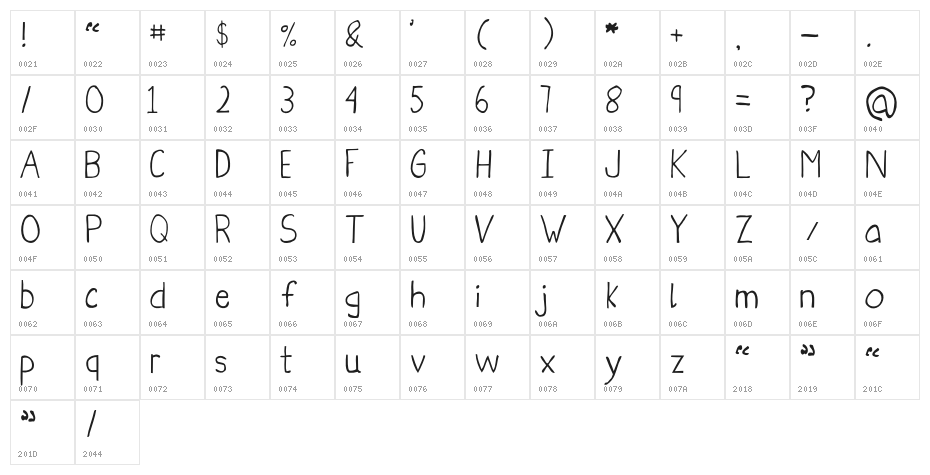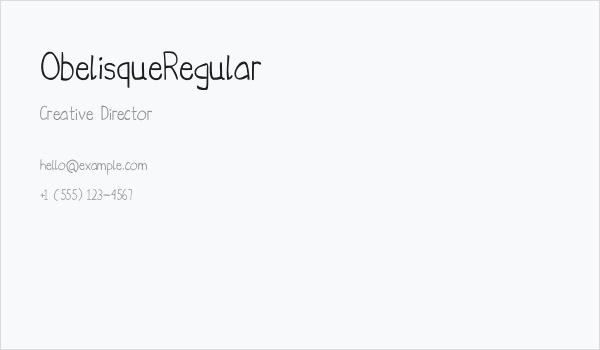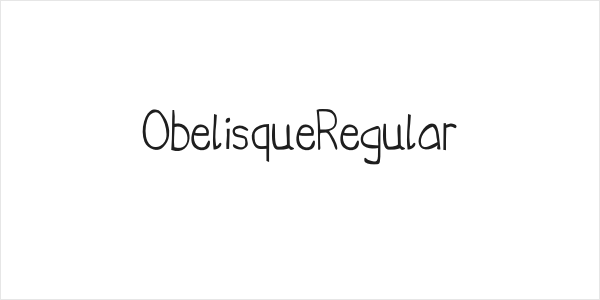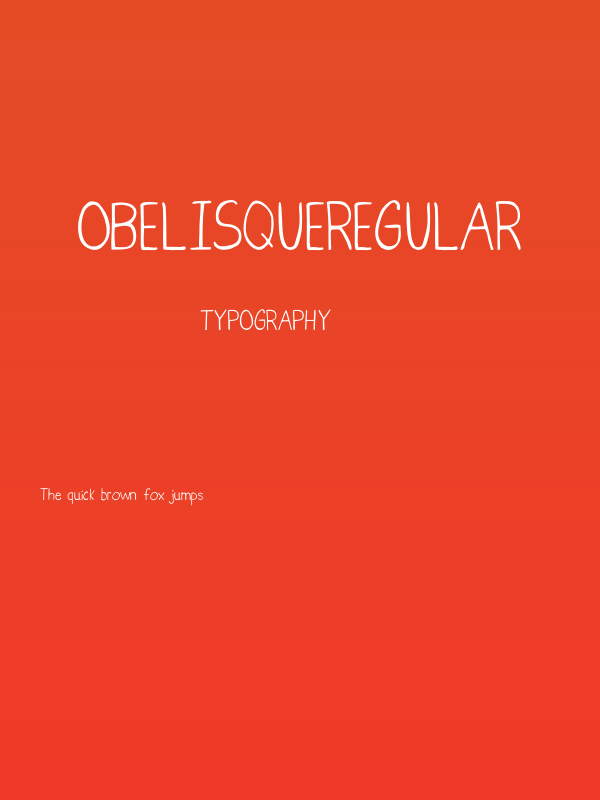
ObelisqueRegular Font
✎ Comic
| Stile generale | Casual and playful |
| Caso d'uso | Headlines, informal text, and creative projects. |
| Progetti proposti | Ideal for greeting cards, children's books, casual branding, and social media graphics. |